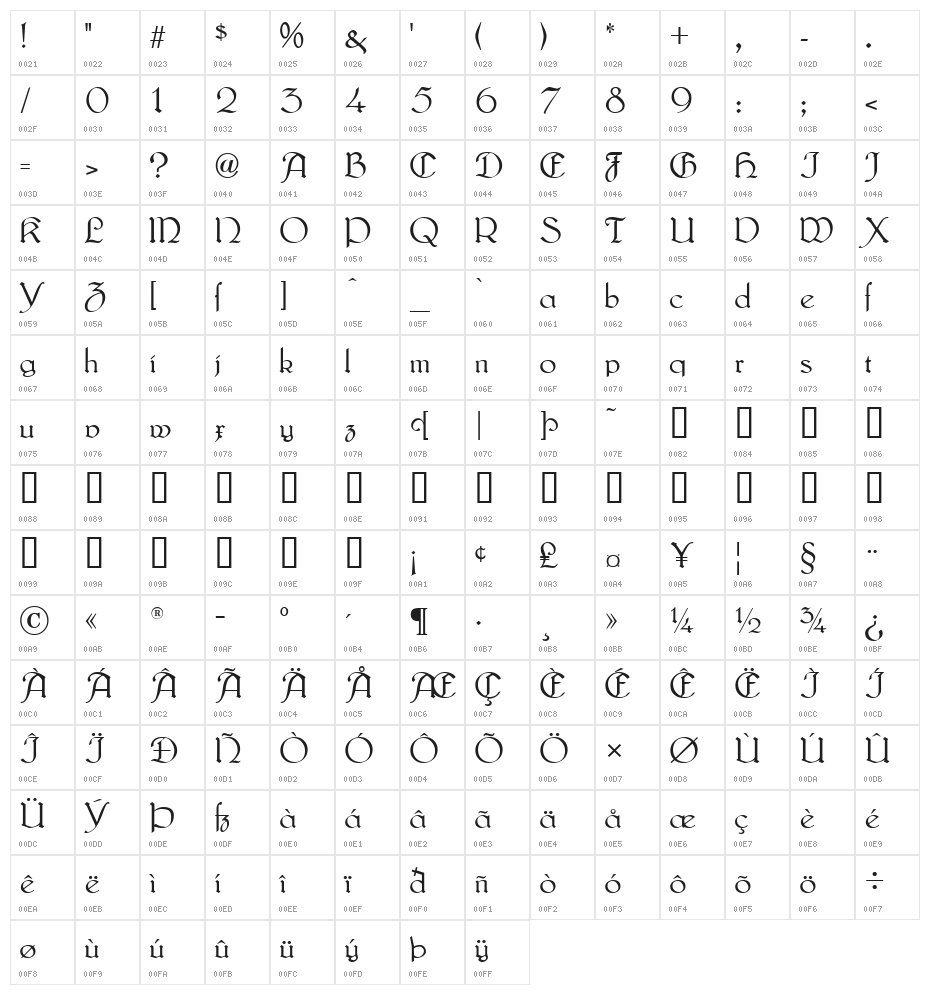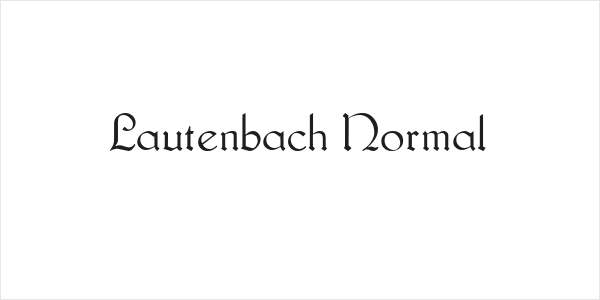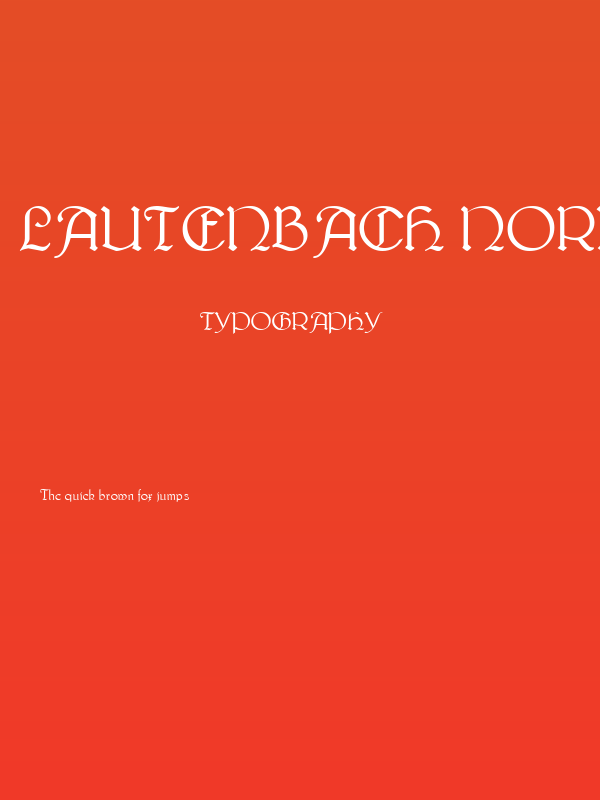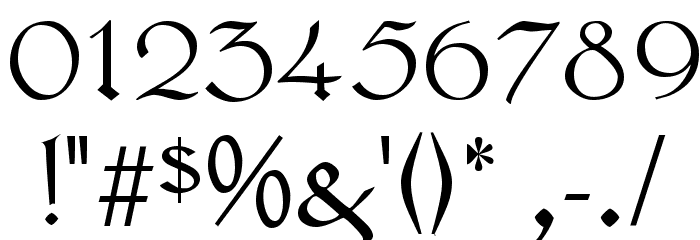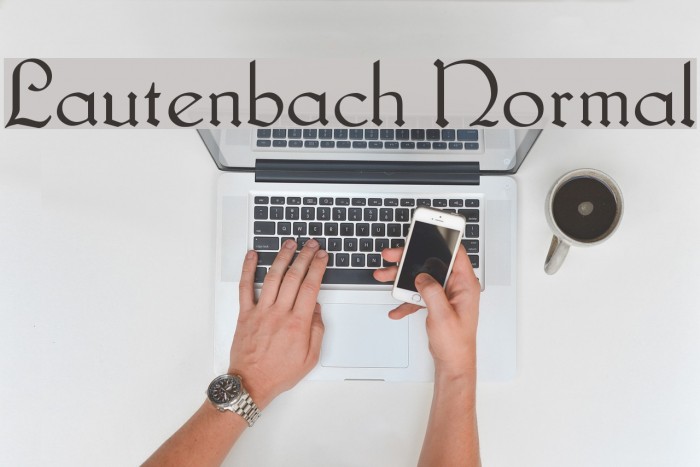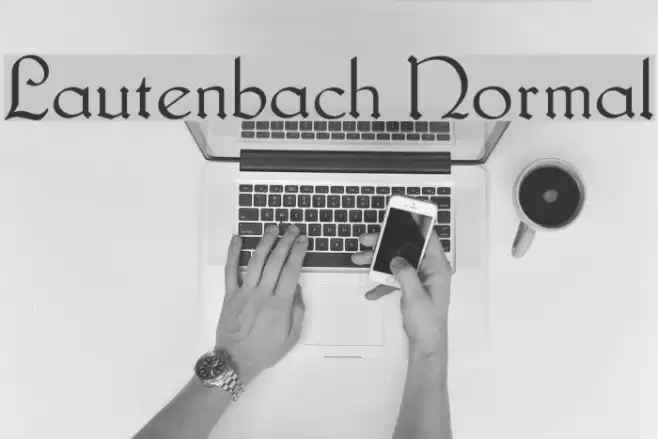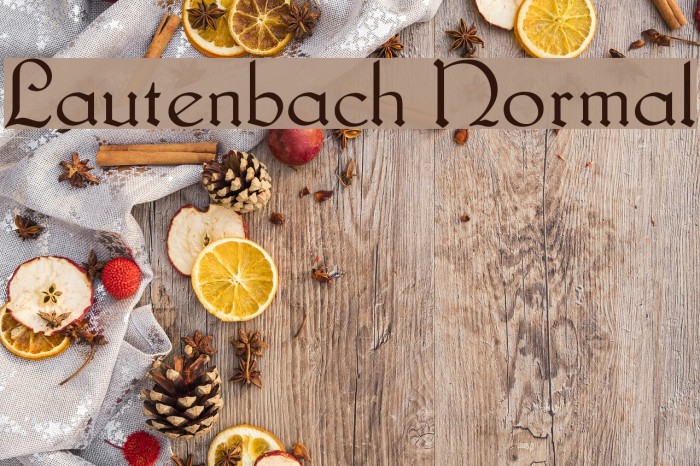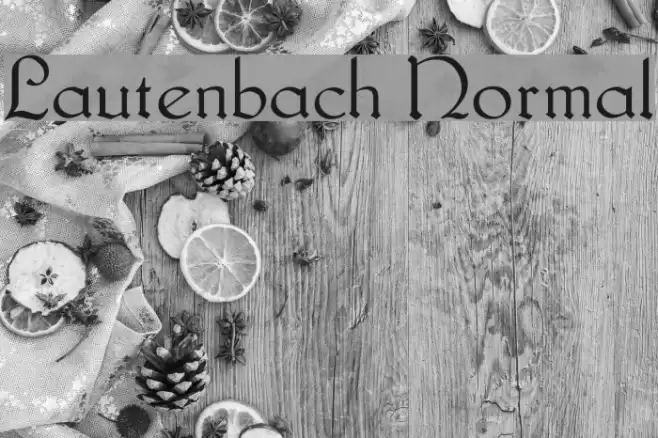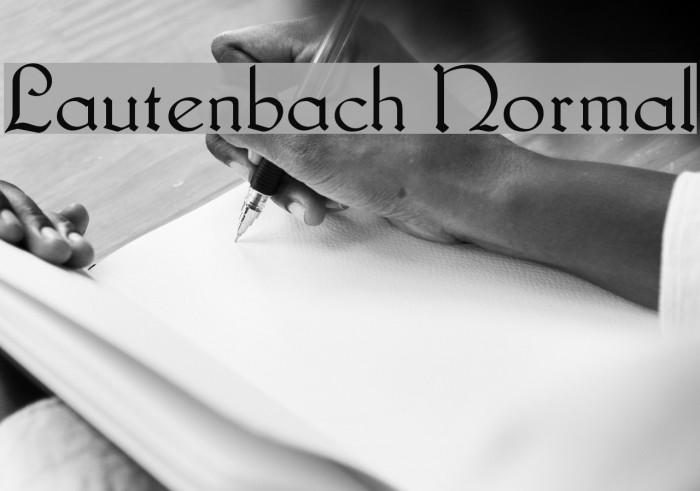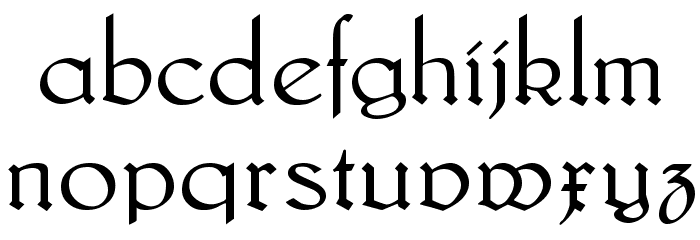
Lautenbach Normal Font
✎ Gothic
| Categorias | Gothic |
| Caso de uso | Logos, Headlines, Decorative text |
| Projetos propostos | Ideal for historical documents, wedding invitations, book covers, and branding that requires a traditional or vintage touch. |